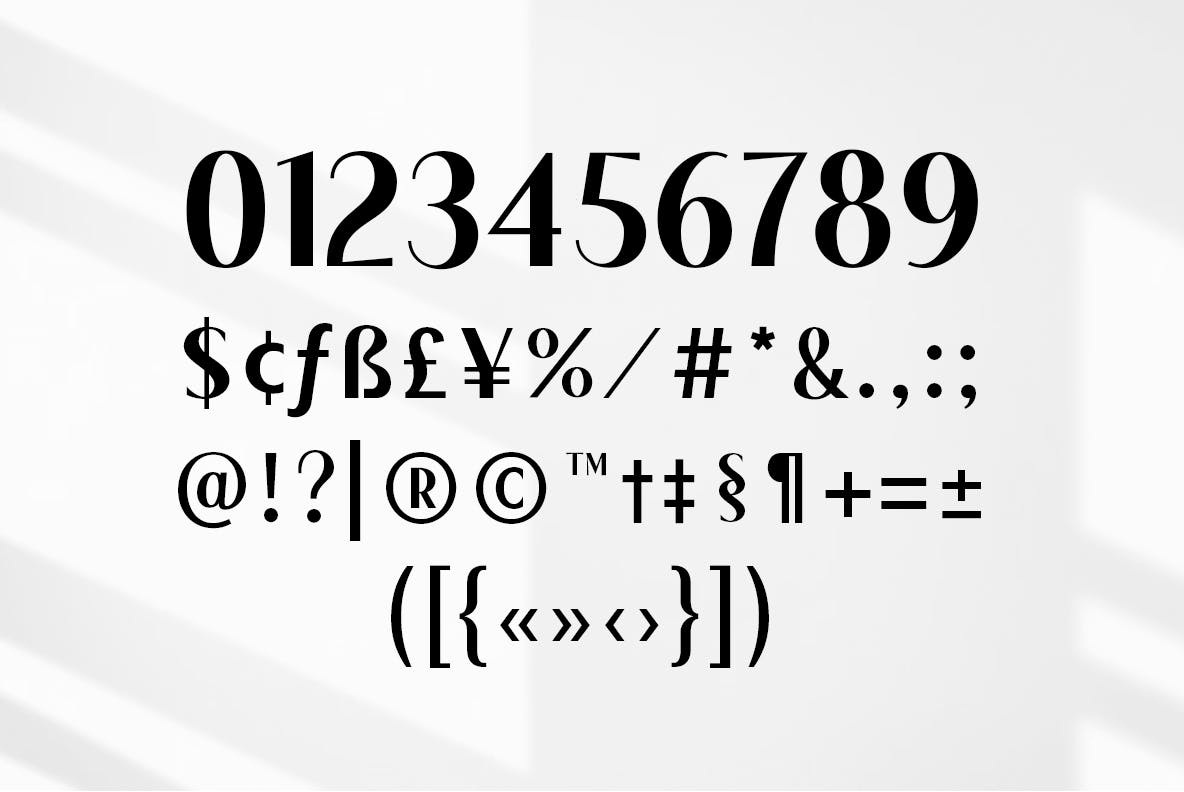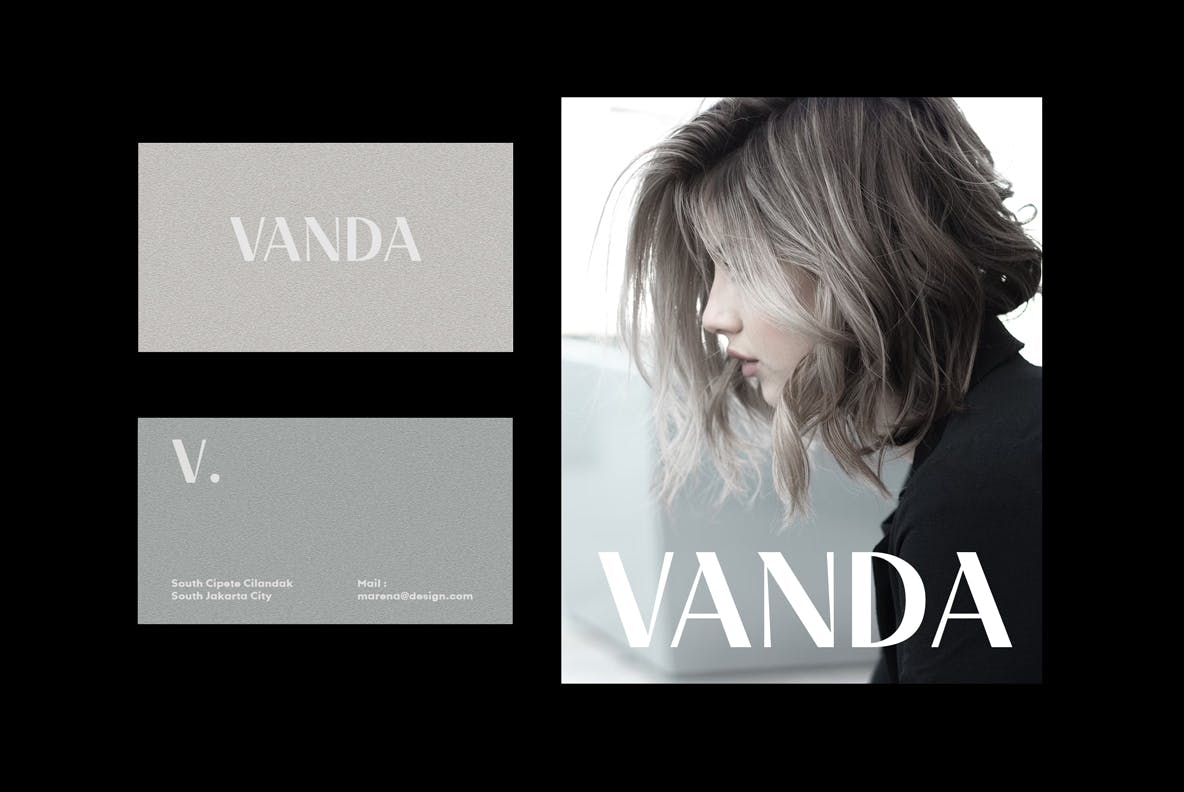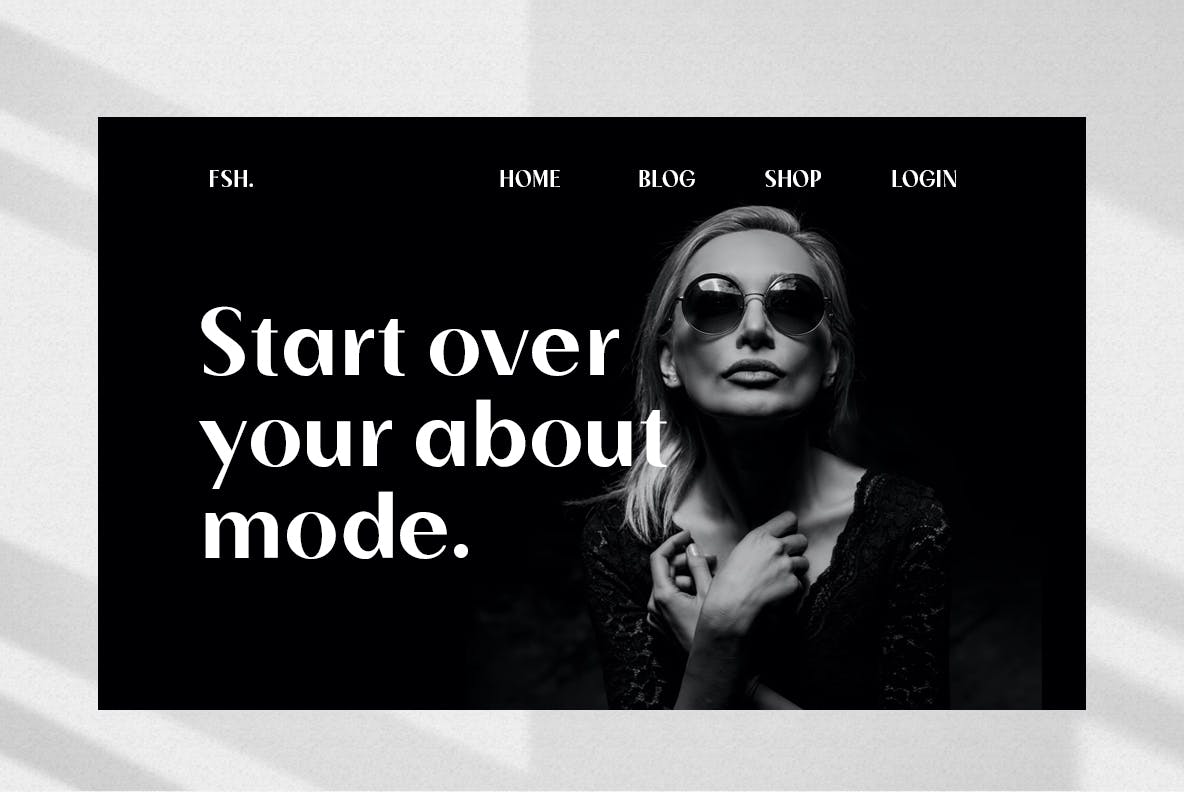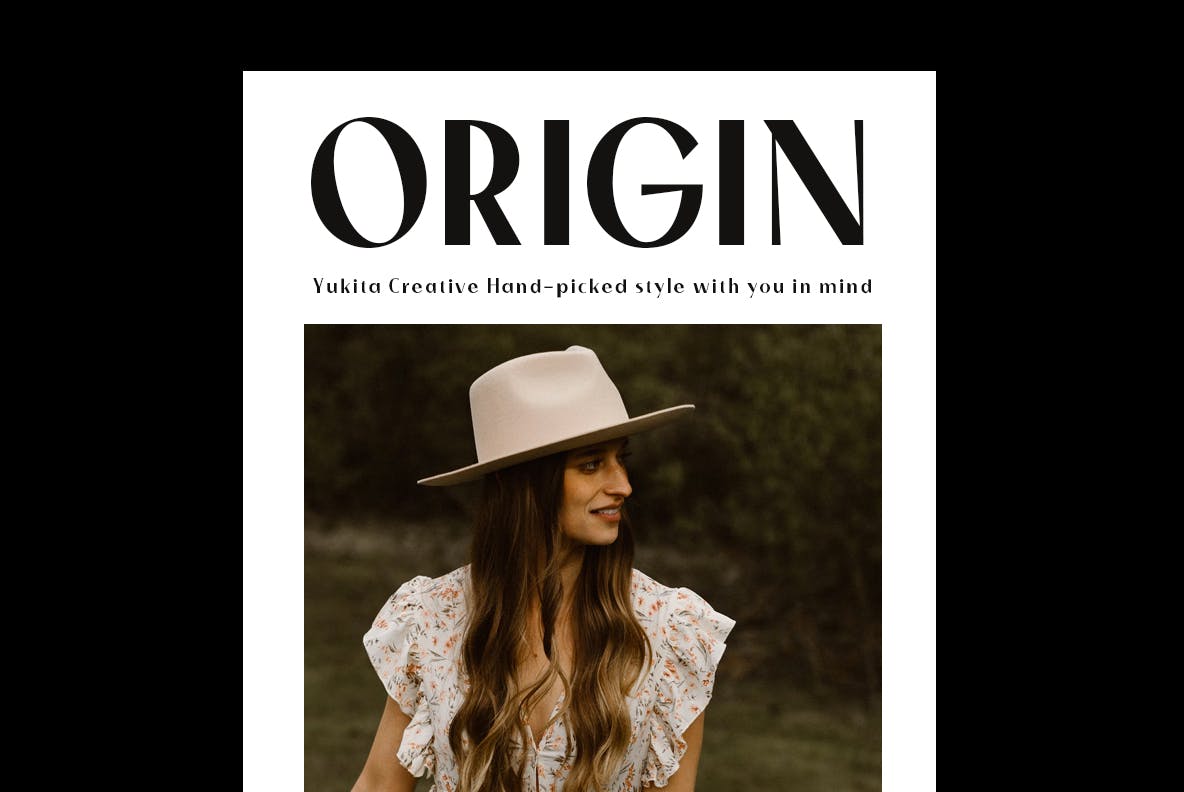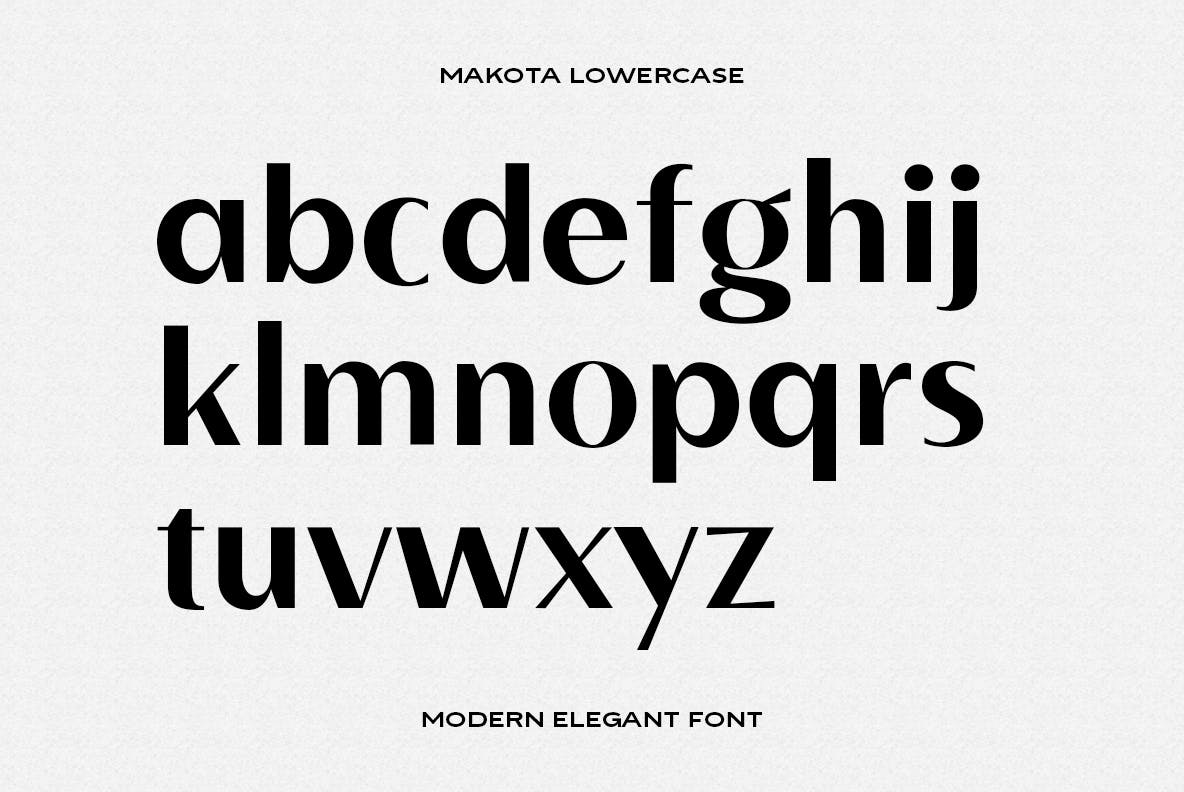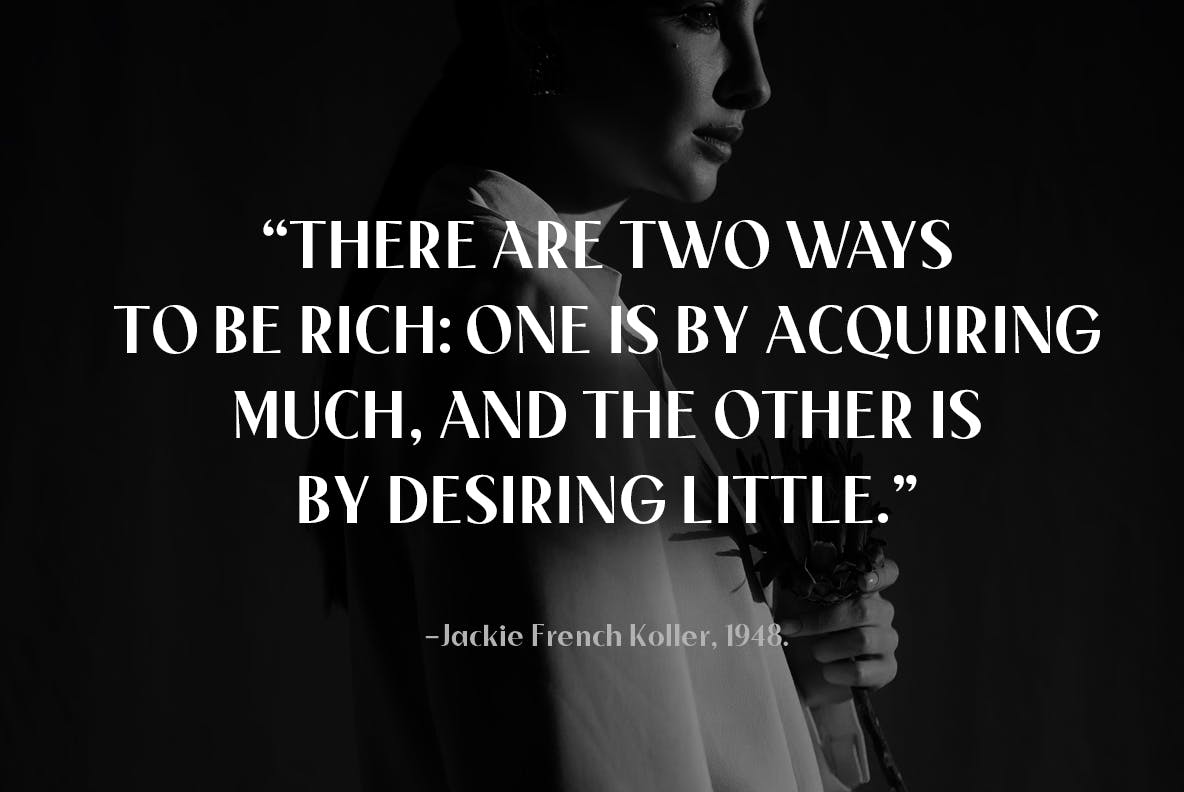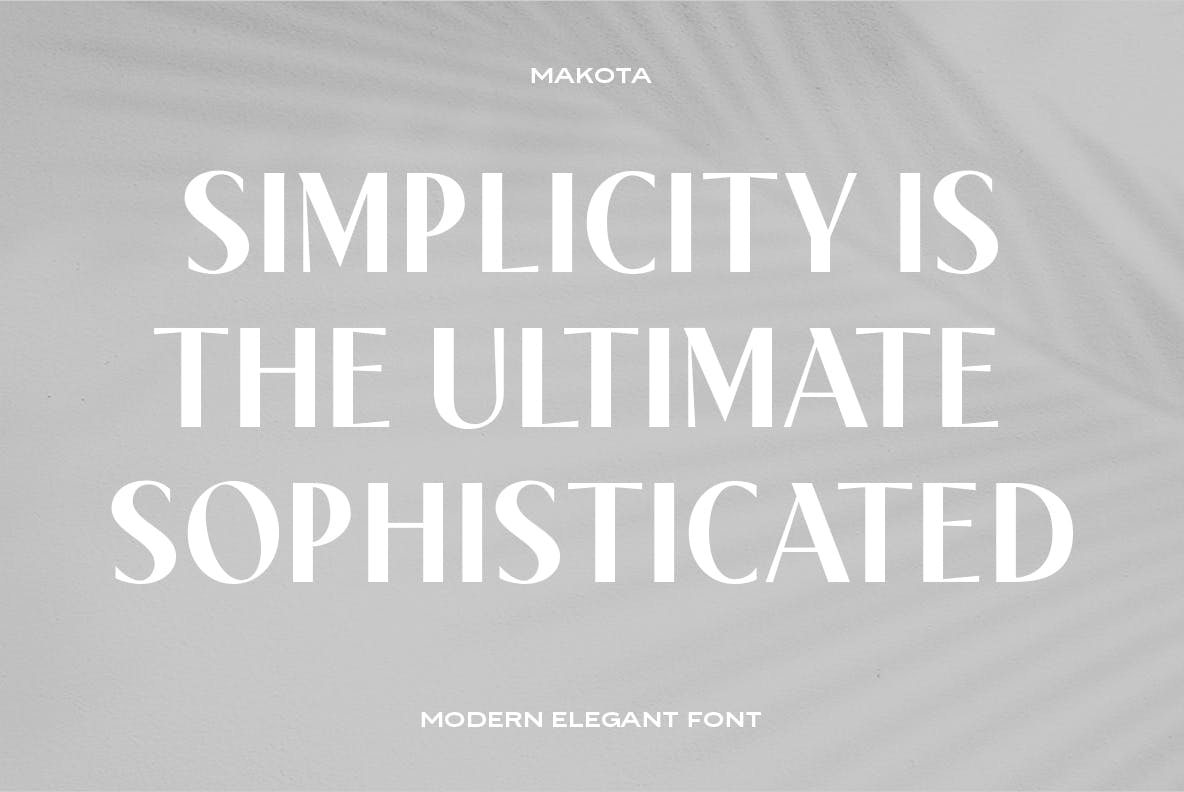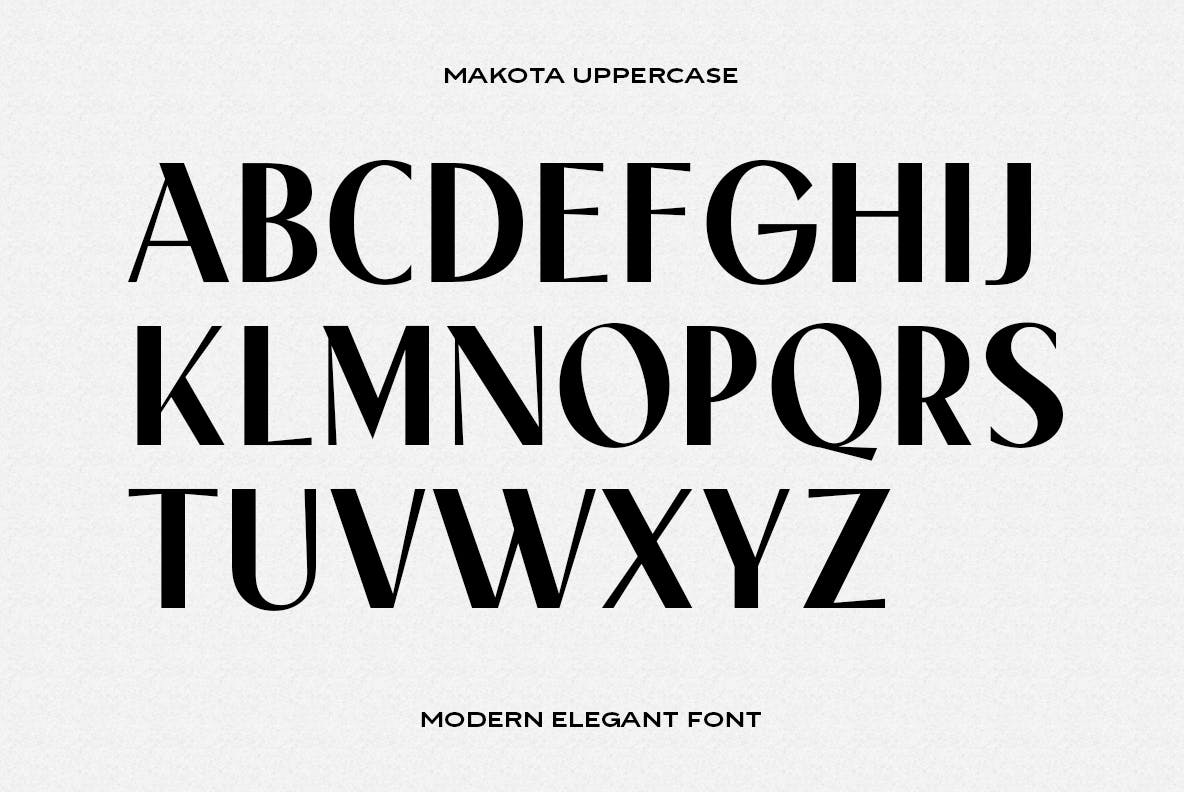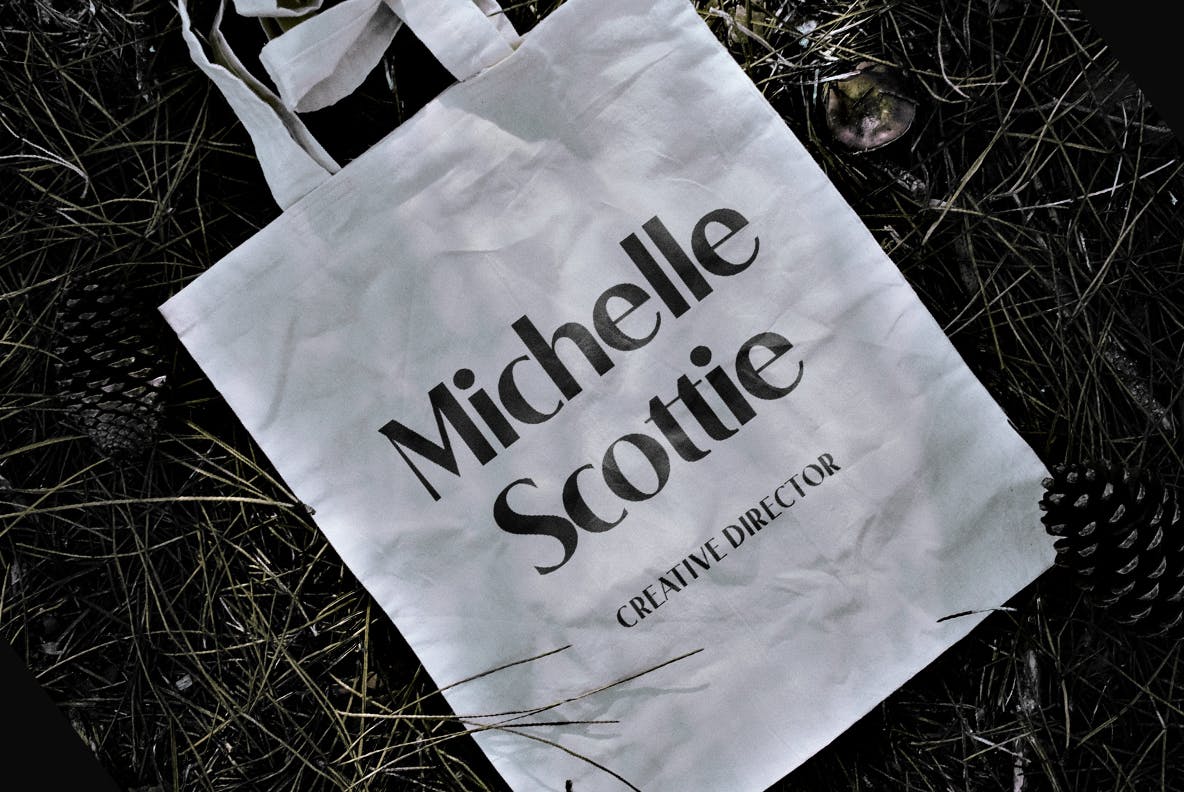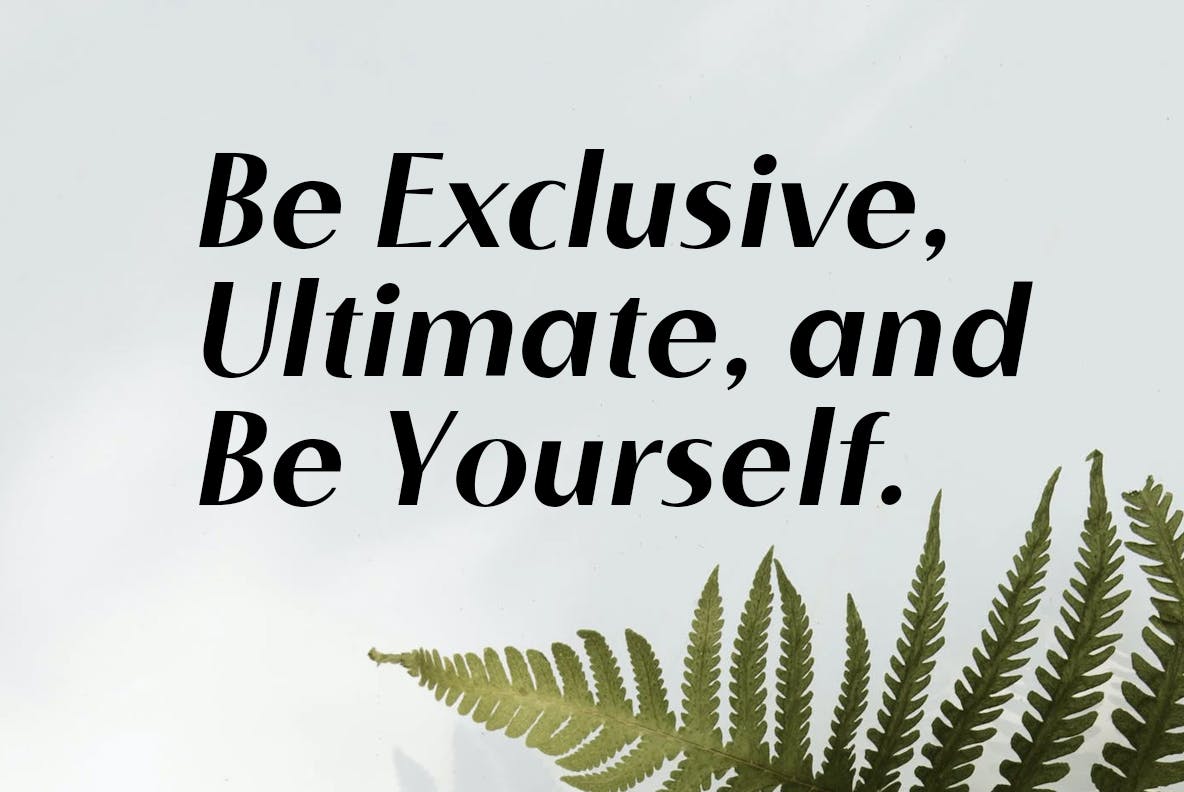
Makota Modern Font
فونت ماکوتا با طراحی زیبا و مدرن، گزینه‌ای ایده‌آل برای پروژه‌های لوکس شماست.
فونت مدرن ماکوتا به‌طور ویژه برای استفاده در پروژه‌های طراحی مرتبط با لوکس بودن طراحی شده است. این نوع‌خوانی بلند و شیک، آن را برای برندینگ و تبلیغات ایده‌آل می‌سازد، در حالی که خوانایی بالای آن، این فونت را برای استفاده در وب‌سایت‌ها، تبلیغات و انواع دیگر ارتباطات مناسب می‌کند.